この象形文字で一言!
iOSアプリにエジプト象形文字を入力できるtadashi atoji氏による無料アプリ「この象形文字で一言!」が登場した。
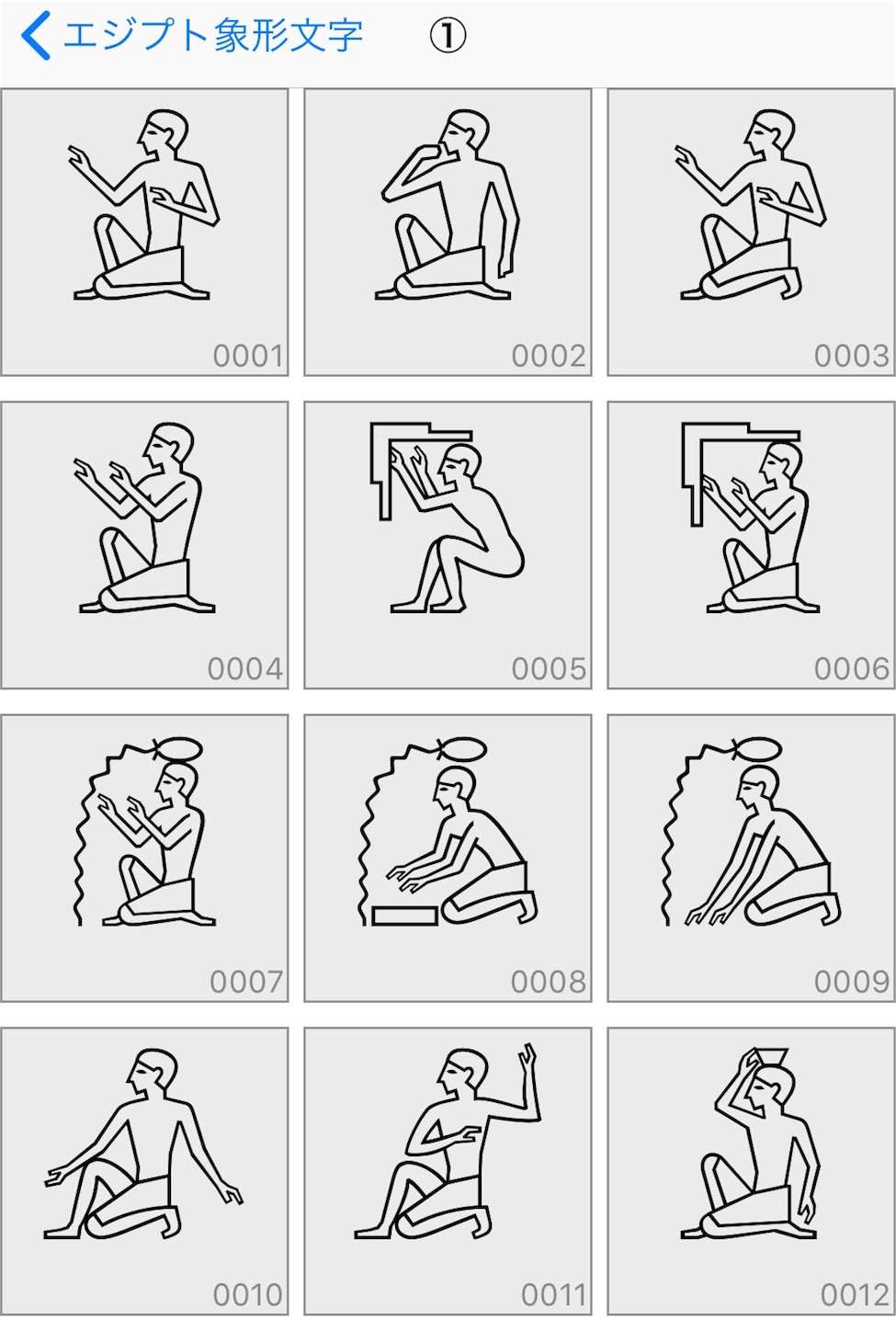
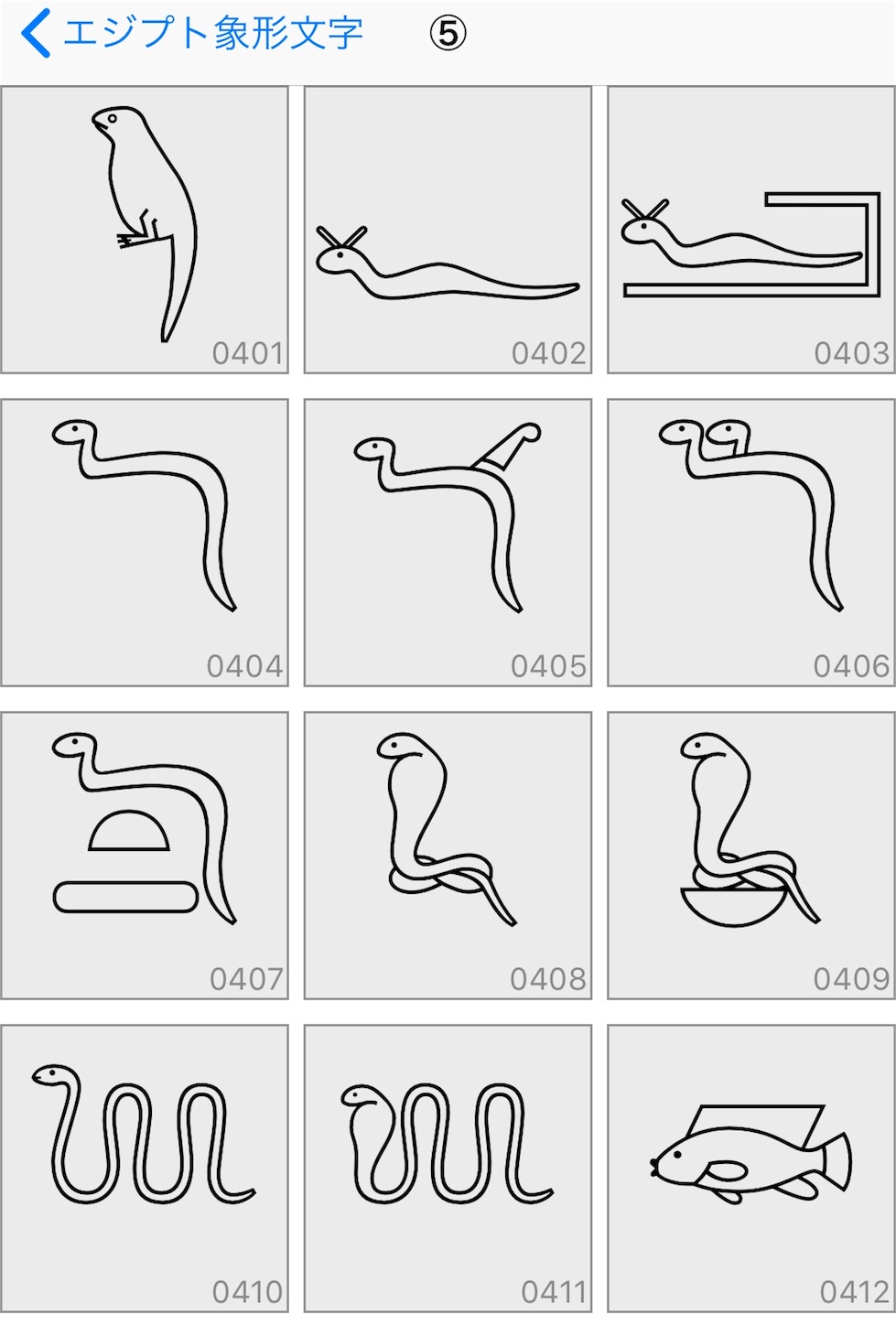
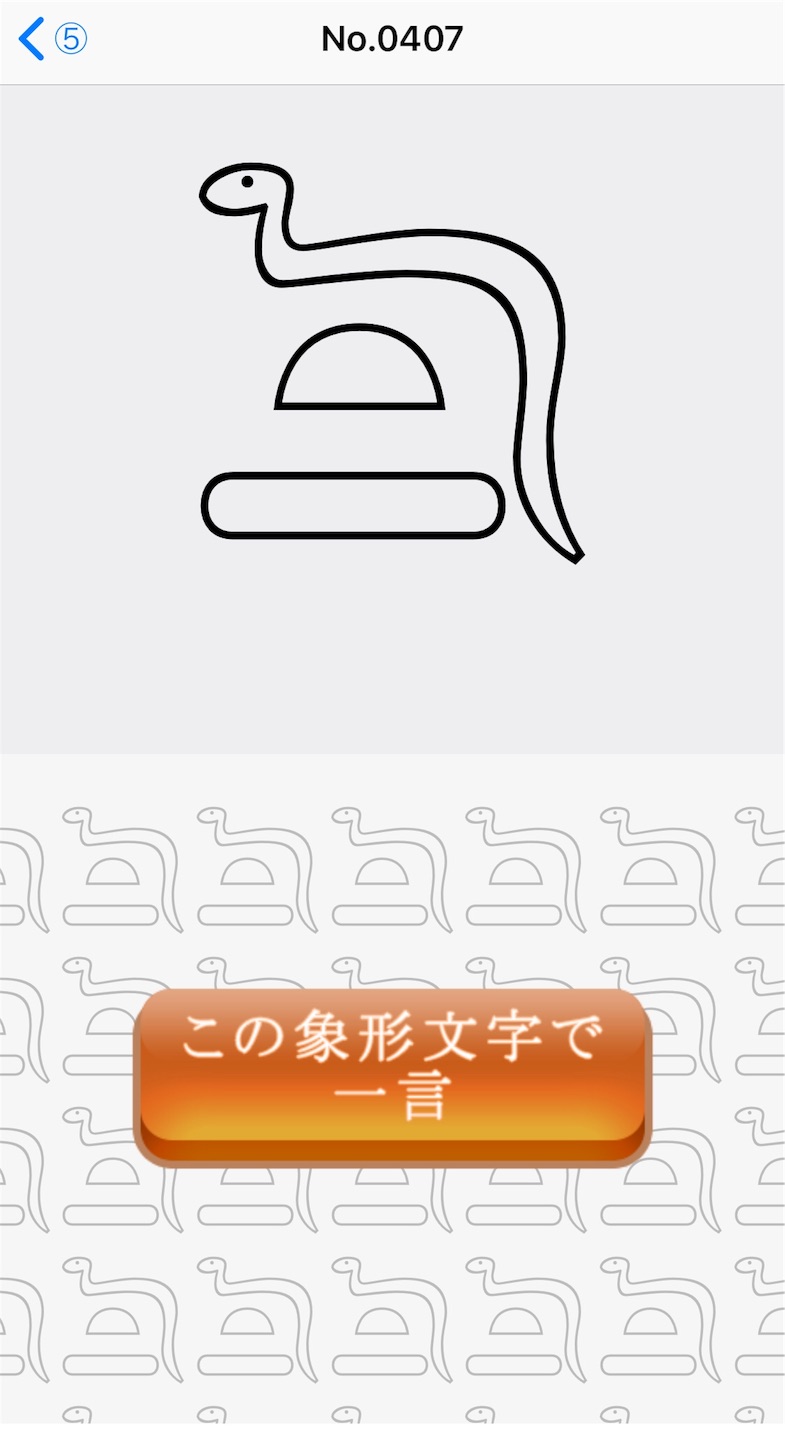
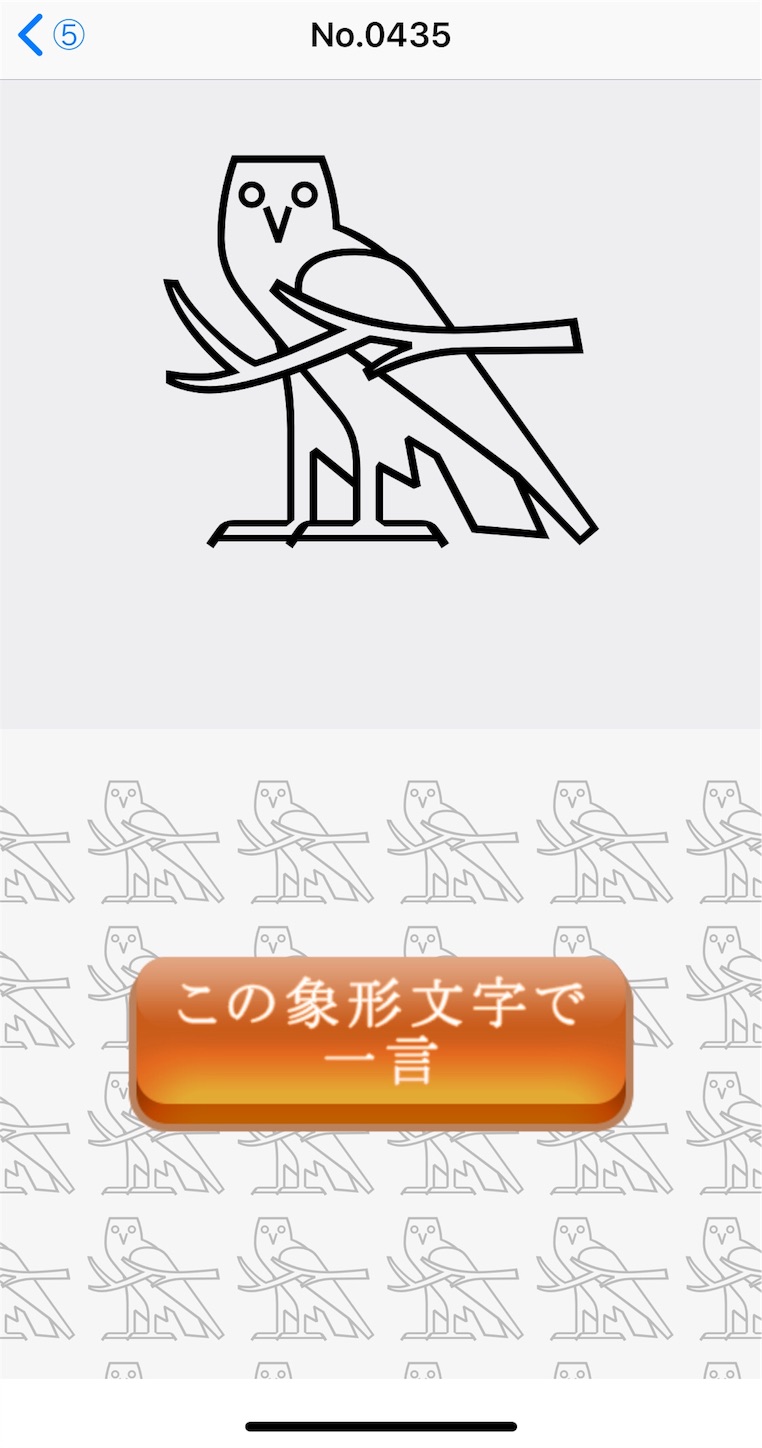
アプリには、全1,071種類あるエジプト象形文字を収録。
その中の象形文字を選んで「この象形文字で一言」でコメントとともにTwitterやFacebookに投稿できる。
また、エジプト象形文字は、iPhone上で、iOS9以降で表示のできる文字としてメモアプリにも書き込むことができ、付属する「エジプト象形文字キーボード」を、iPhoneの設定から追加することで、どのアプリでもエジプト象形文字を入力することができるようになる。
見てるだけで吹き出しそうになるエジプト象形文字。
いったいどんな意味を持っていたのか、、眺めて考察するのも面白い。
このアプリでは、全1071種類あるエジプト象形文字を、ひとつひとつじっくりと観察することができます。
大きな画像付きで投稿できる様になっていますので、実際の文字を表示できない機種でも、見ることができますよ。
このエジプト象形文字は、iPhone上では、iOS9以降で表示のできる文字の1種類で、メモアプリにも書き込むことができます。
付属する「エジプト象形文字キーボード」を、iPhoneの設定から追加することで、どのアプリでもエジプト象形文字を入力することができるようになります。(が、使い道があるのかはわかりません。)
最古の絵文字とも言える、エジプト象形文字の世界を、お楽しみください。